仅需一台电脑,一些不错的字体和一些想象力,您就可以创建一些出色的排版数字贺卡或海报。
下面的列表是手工组合而成的字体,装饰符号,大胆的粗体字体和异想天开的字体,这些都将为您的创作增添光彩。
如果您要使用异想天开的选项,前三种字体是一个不错的选择:
1。 Windsong
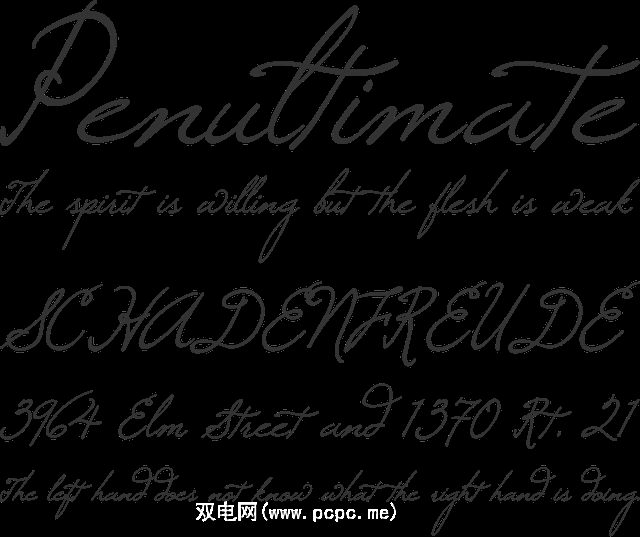
2。 Fabfelt
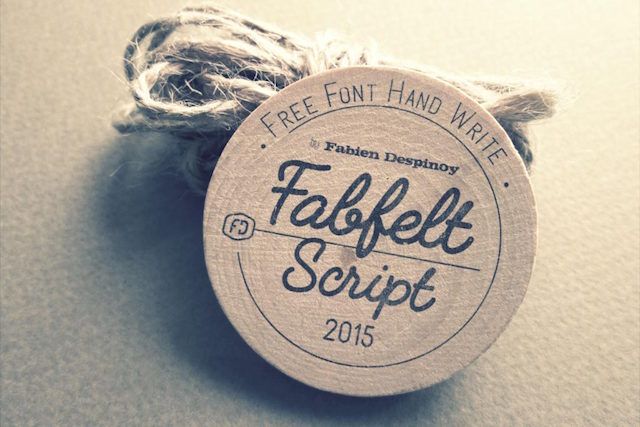
3。 Janda Happy Day
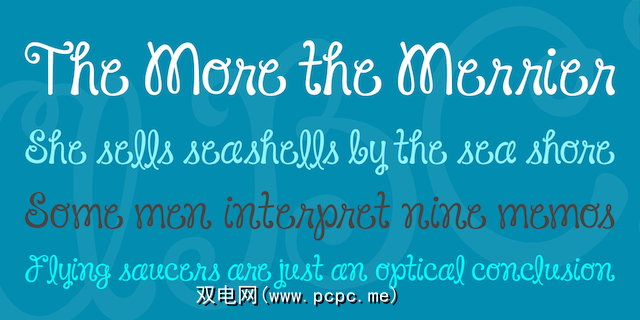
如果您正在寻找更简单的东西,这些字体可能会有用:
4。 Fox&Cat
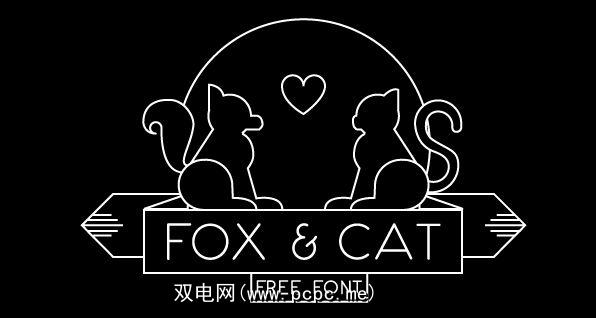
5。安德斯(Anders)
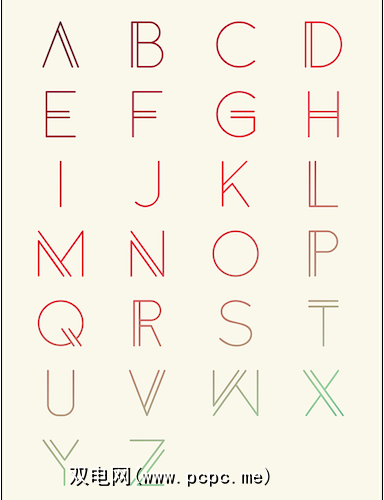
对于大胆的情感,有以下三种选择:
6。块
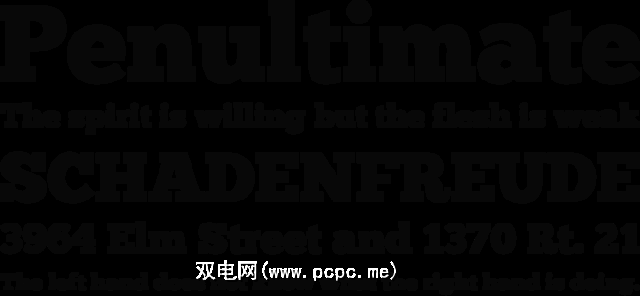
7。 Brusher
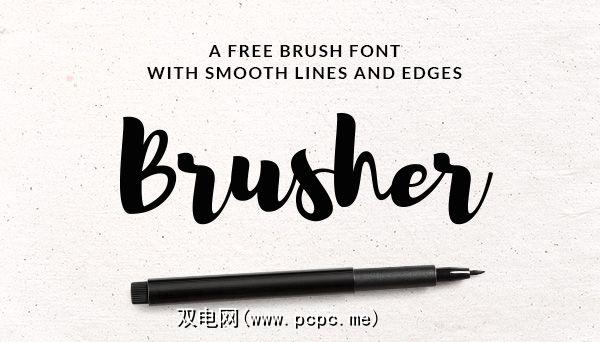
8。 Zenfyrkalt
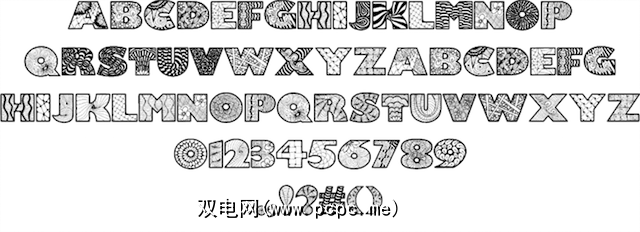
Dingbat字体对于我们这些不具备最出色艺术技能的人来说是一种简便的方法,可以为您的作品添加一些可爱的图画。
9。贝拉D
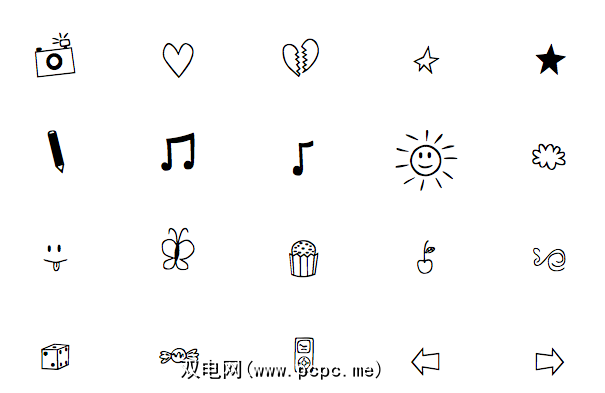
10。心脏涂鸦
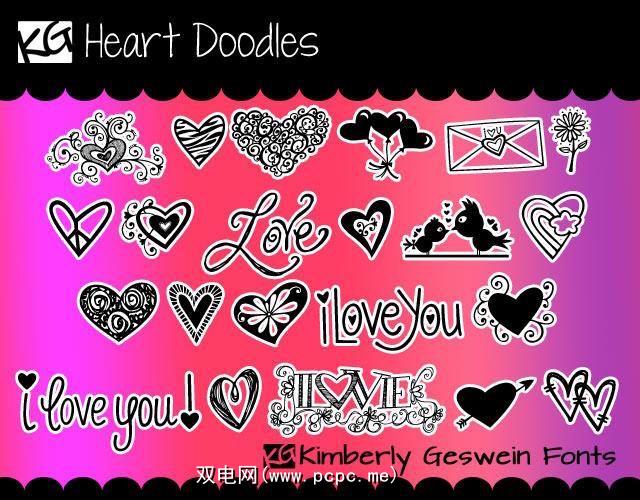
11。小胡子
12。 Pea Jelene的Doodles
13。 KG圣诞树字体
14。 MFT Itty Bitty Baby